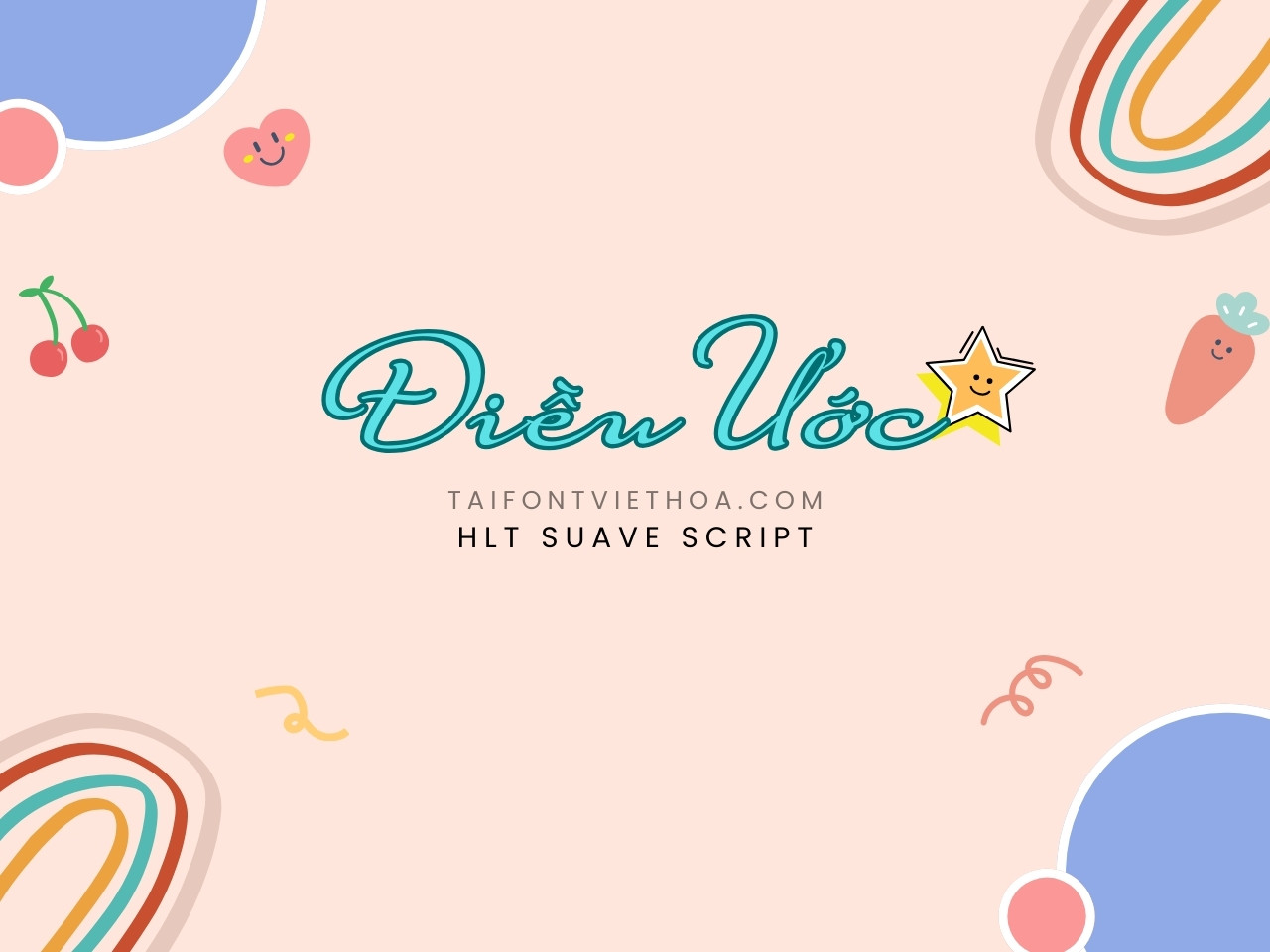
HLT Suave Script – Nét quyến rũ từ chữ viết tay hiện đại
HLT Suave Script là phiên bản Việt hóa từ font gốc “Suave Script” – một kiểu chữ mang phong cách handwritten script hiện đại, do phông chữ này được phát triển bởi nhà thiết kế nước ngoài chuyên về chữ ký nghệ thuật và typography cá nhân hóa. Font gốc nổi bật trên các nền tảng như Creative Market, hỗ trợ hơn 60 ngôn ngữ Latinh, phục vụ tốt cho thị trường toàn cầu.
Phiên bản Việt hóa được thực hiện bởi đội ngũ HLT Fonts, đảm bảo đầy đủ bảng ký tự tiếng Việt có dấu, tương thích hoàn hảo với Unicode. Font vẫn giữ nguyên sự mềm mại và chuyển động tự nhiên của nét bút tay, đồng thời được tinh chỉnh để phù hợp với nhu cầu sử dụng trong thiết kế đồ họa tiếng Việt. Bộ font HLT Suave Script được taifontviethoa.com chọn lọc kỹ lưỡng, kiểm thử trên nhiều nền tảng và chia sẻ nhằm phục vụ các designer yêu thích phong cách viết tay nghệ thuật ứng dụng trong thực tế dự án cá nhân và thương mại.
Vẻ đẹp mềm mại và ứng dụng nổi bật của HLT Suave Script
Font HLT Suave Script sở hữu các đường nét mượt mà, mô phỏng chuyển động tự nhiên của nét bút brush hoặc bút lông. Cấu trúc chữ nghiêng nhẹ, độ dày thay đổi linh hoạt giữa các nét chính – phụ, mang lại cảm giác uyển chuyển, nữ tính nhưng vẫn rõ ràng. Các glyphs còn được trang bị thêm các ký tự thay thế (alternates) giúp tạo điểm nhấn cá nhân và sinh động trong từng dòng chữ.
Font này cực kỳ lý tưởng cho các thiết kế thiệp mời, thiệp cưới, chữ ký logo, tiêu đề trong các poster sự kiện, cũng như các ấn phẩm truyền thông dành cho spa, thời trang, mỹ phẩm hoặc nội dung có yếu tố cá nhân hóa cao. Phong cách viết tay bay bổng, gần gũi của HLT Suave Script giúp thiết kế trở nên thân thiện và thu hút.